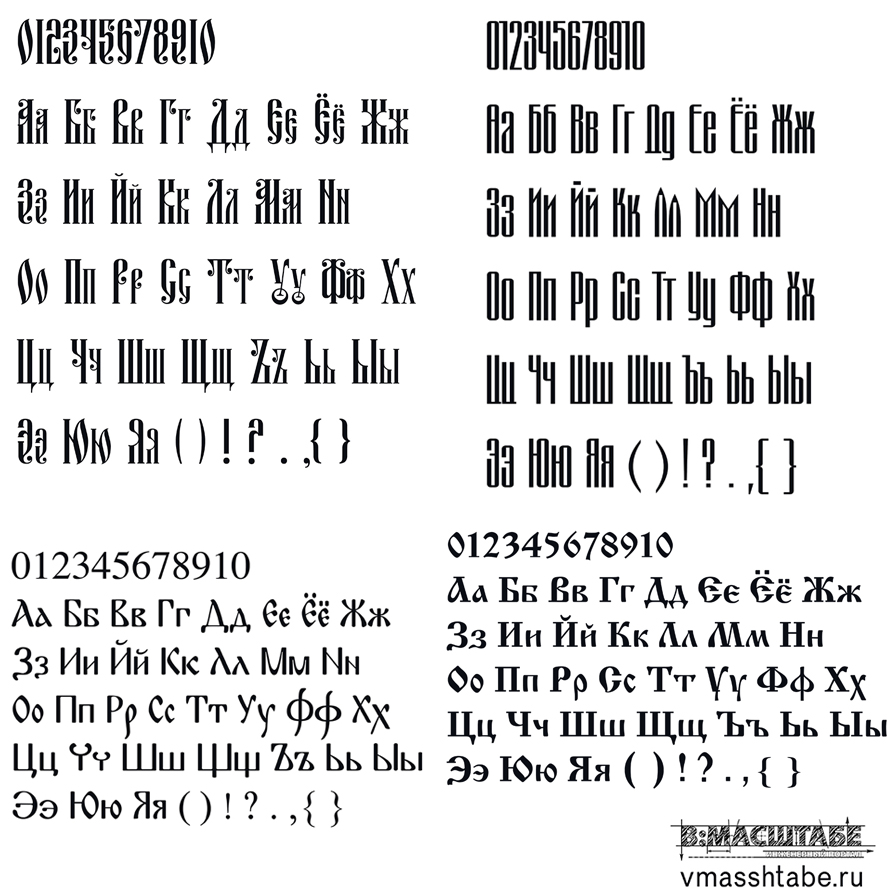
Цифры и Алфавит. Прописные и строчные латинские буквы. Для оформления надписей декора. Контурный Шрифт для резки на чпу.
Шрифт трафаретный Славянская тематика
Славянская тематика в письме интересна.